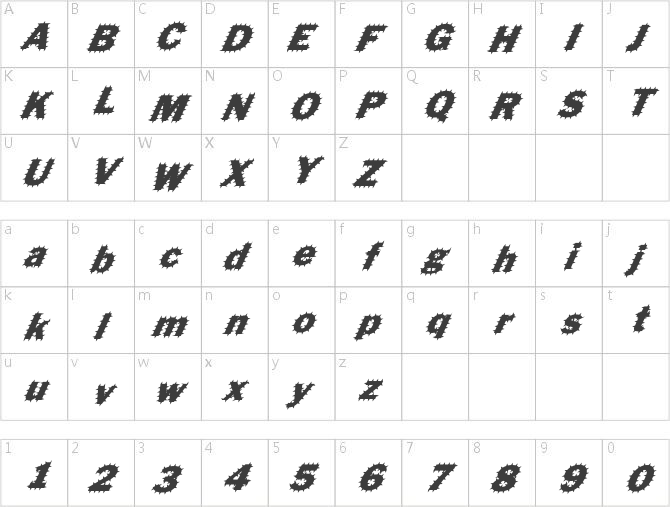
FZ BASIC 56 SPIKED ITALIC
FZ BASIC 56 SPIKED ITALIC介紹
FZ BASIC 56 SPIKED ITALIC字體字庫是一款讓人賞心悅目、百看不厭的英文字體,適合各類廣告和產品包裝設計應用,字體大小0.09MB,格式為ttf字體,上傳用戶是浪跡天涯,作者/版權方為未知